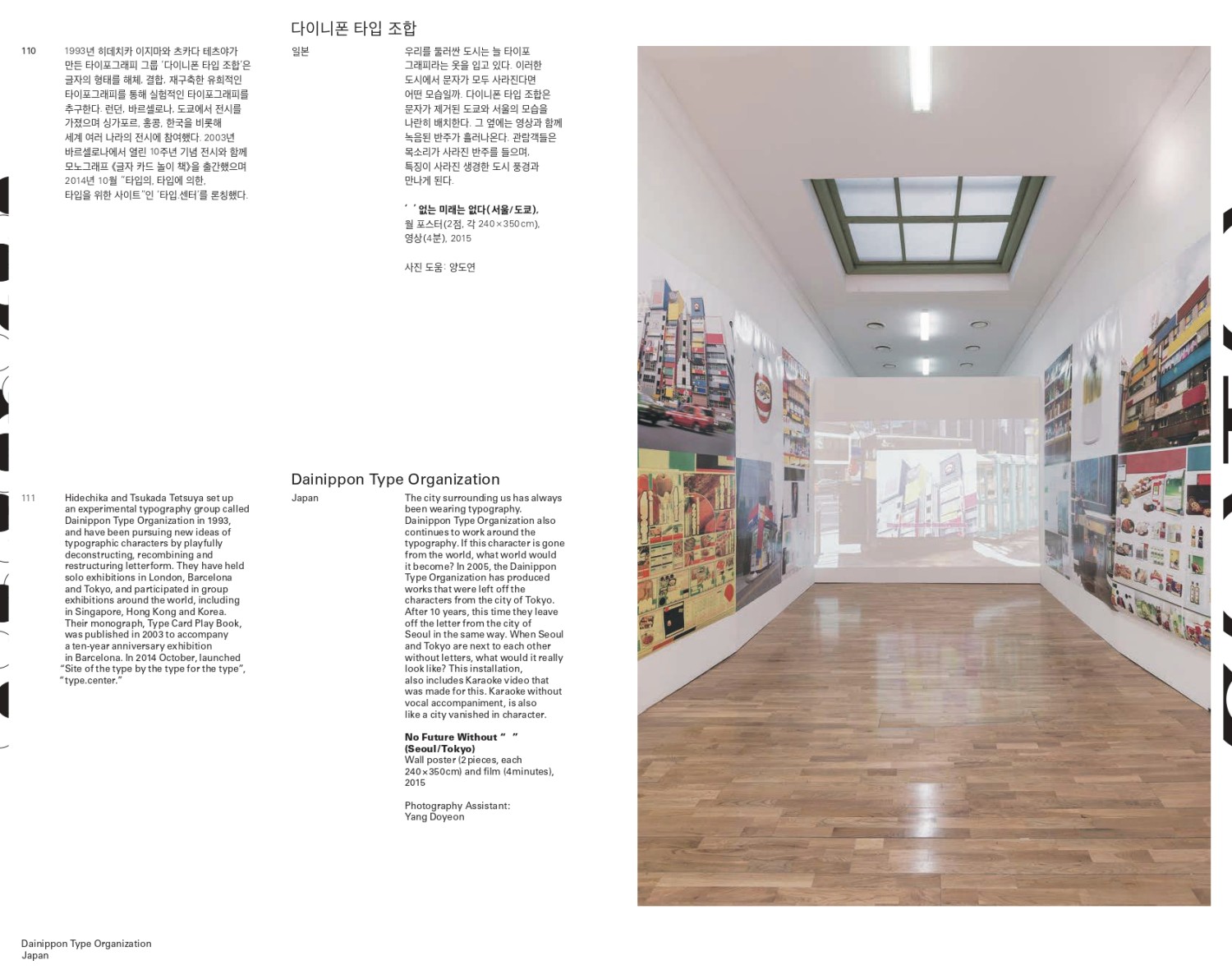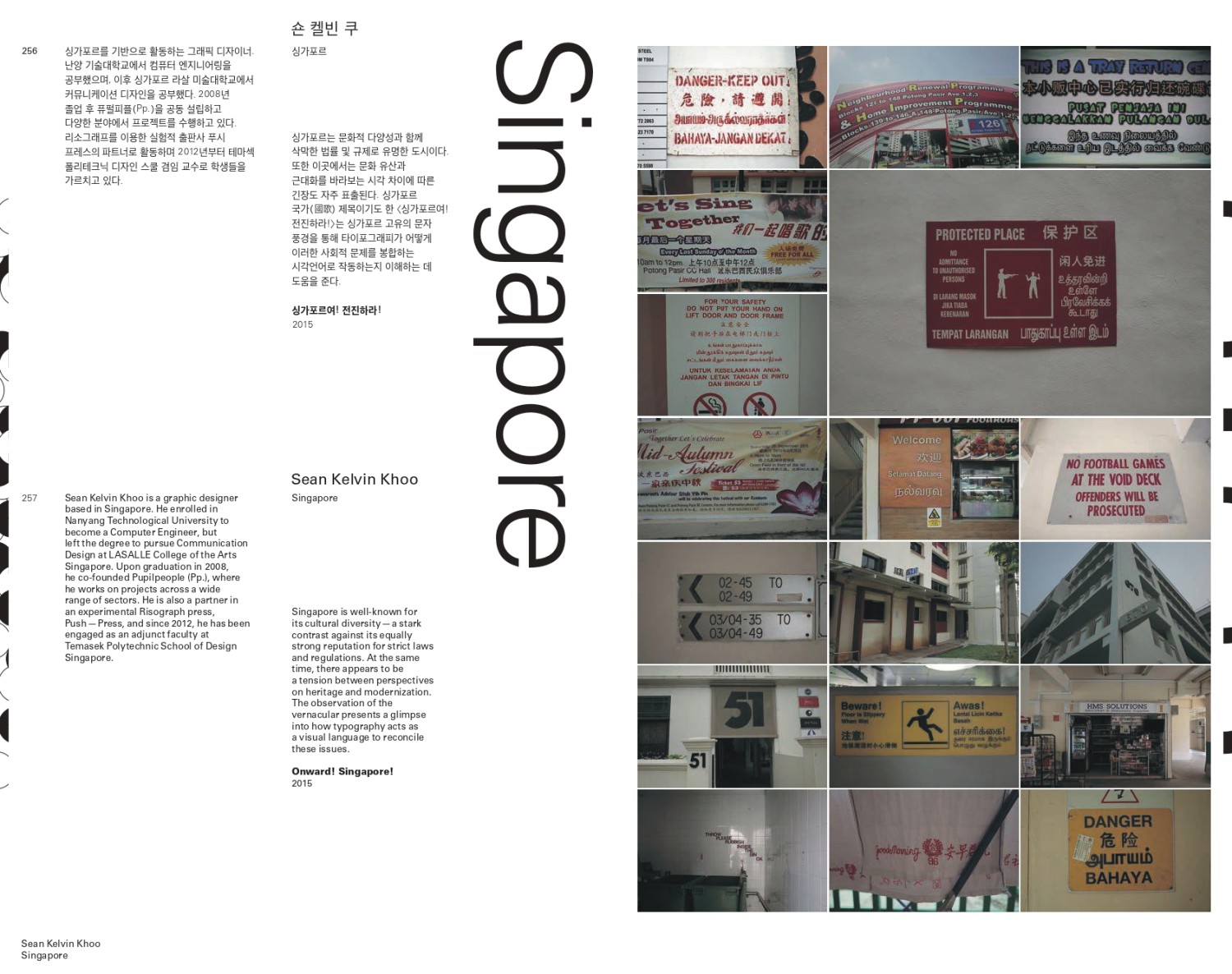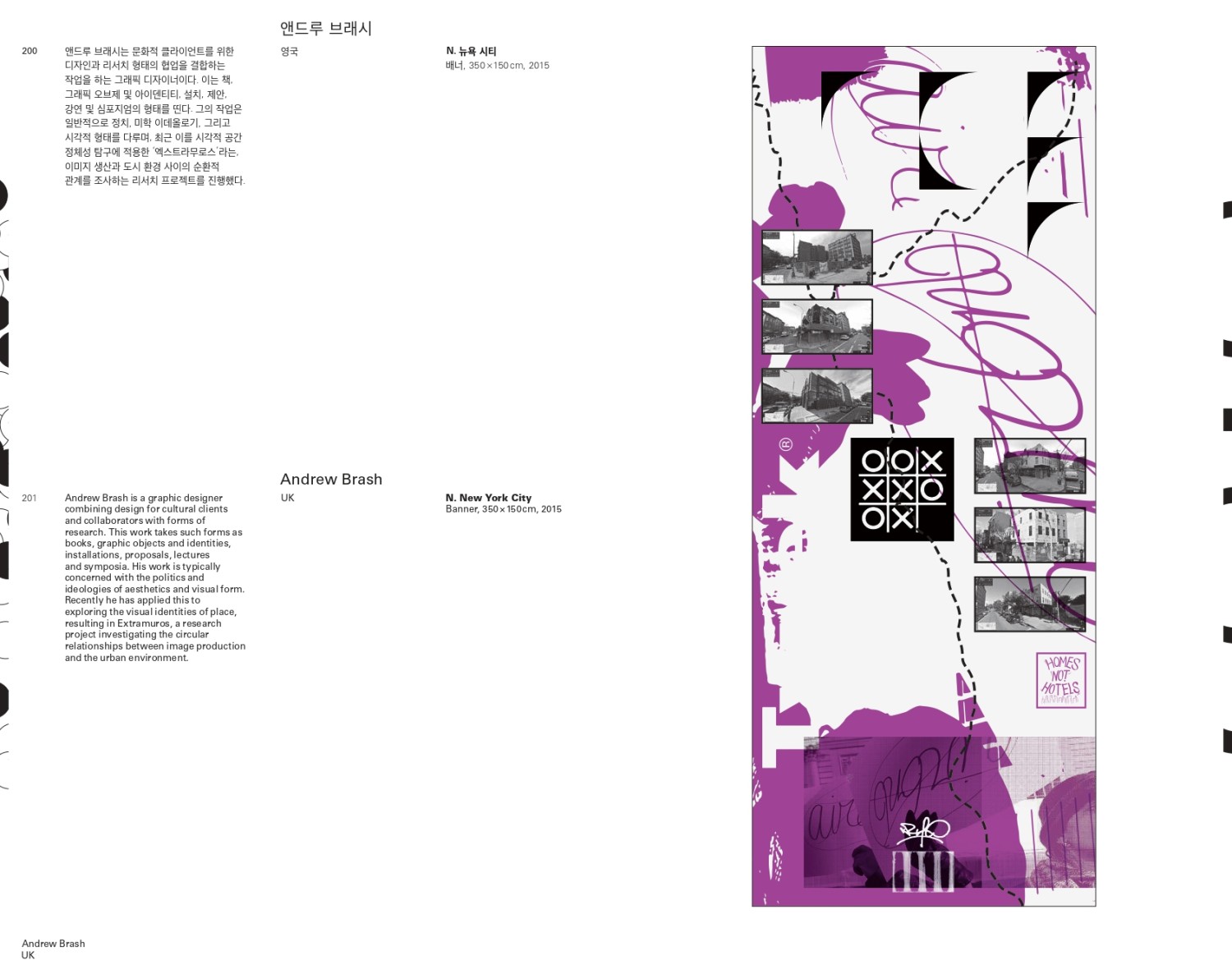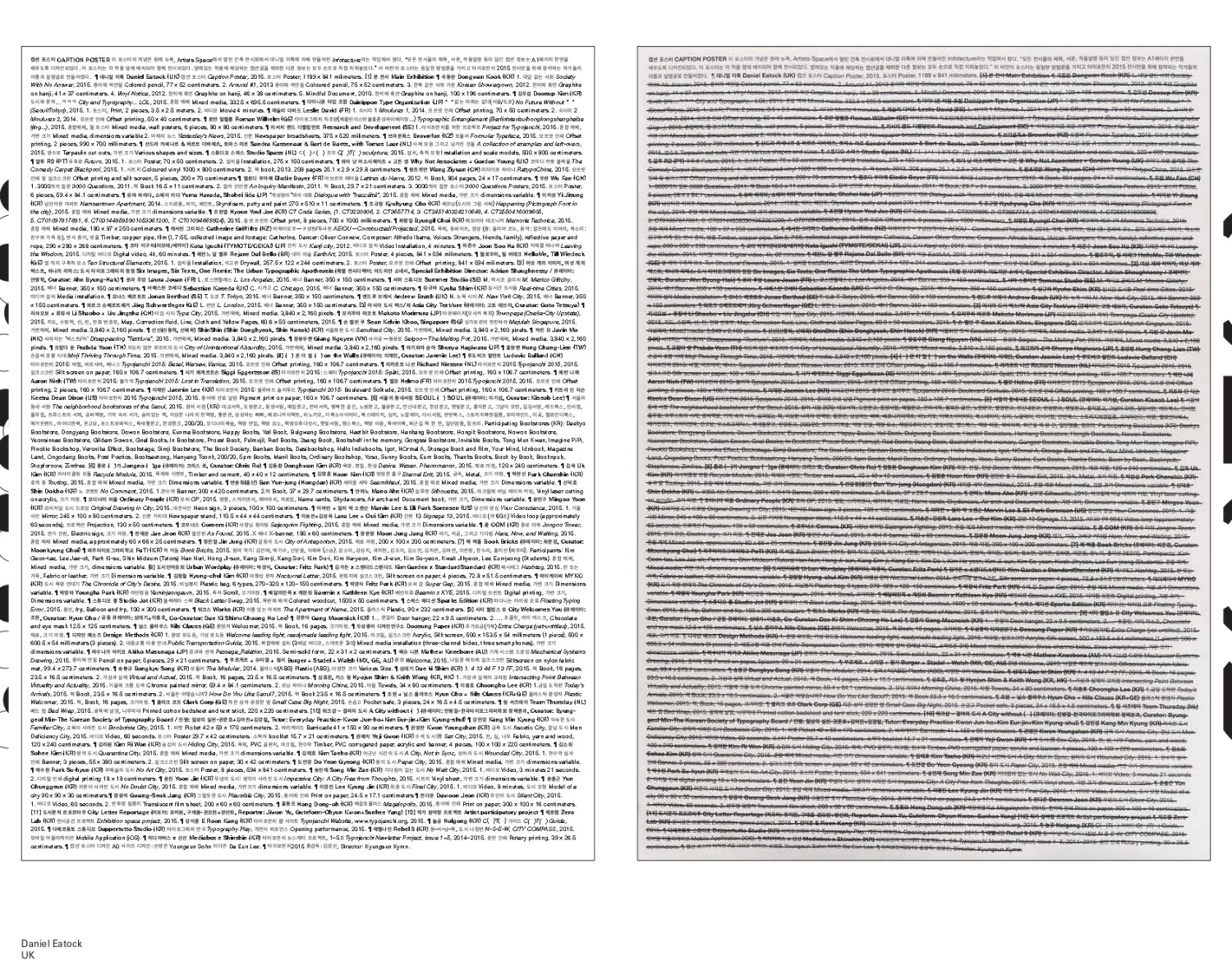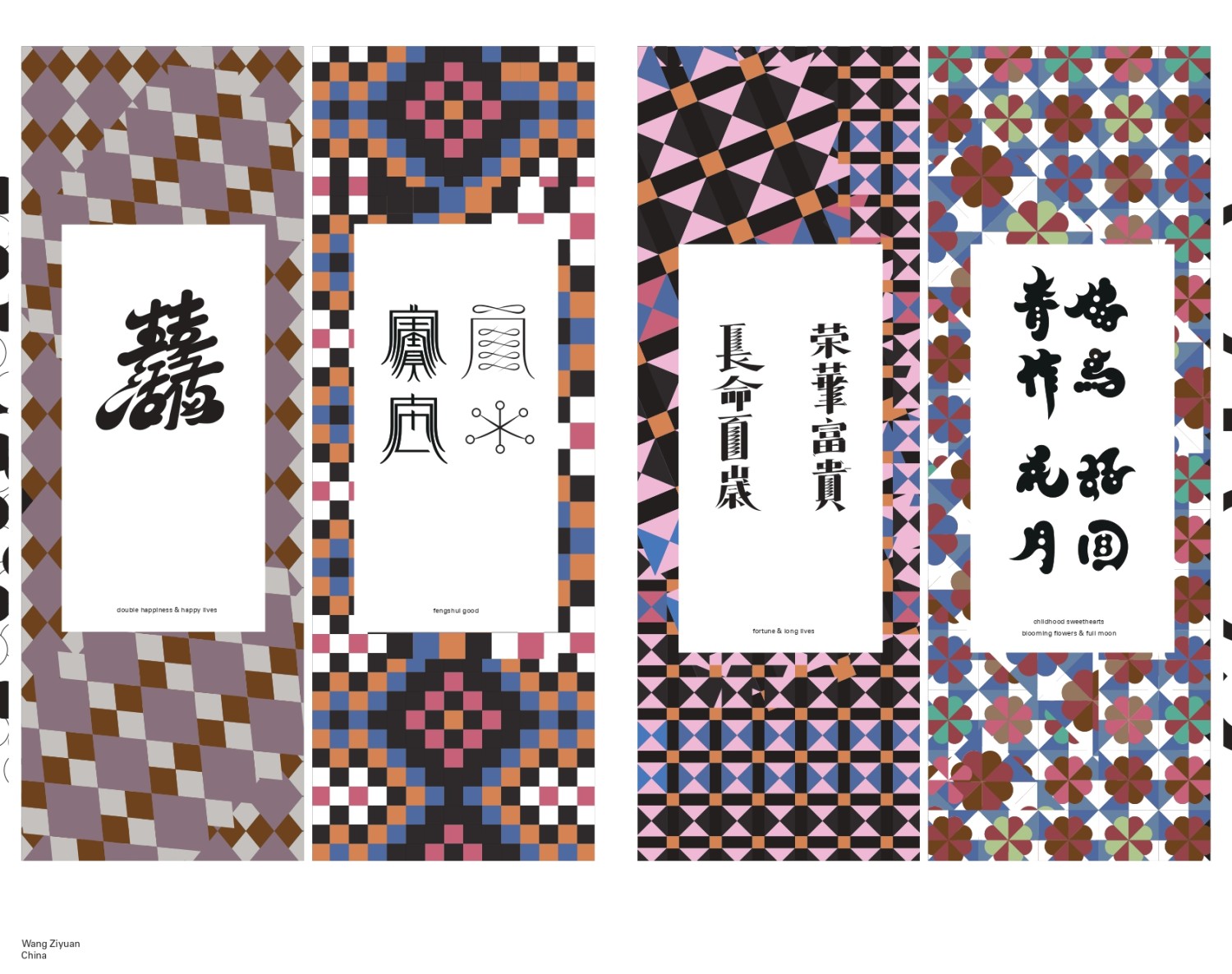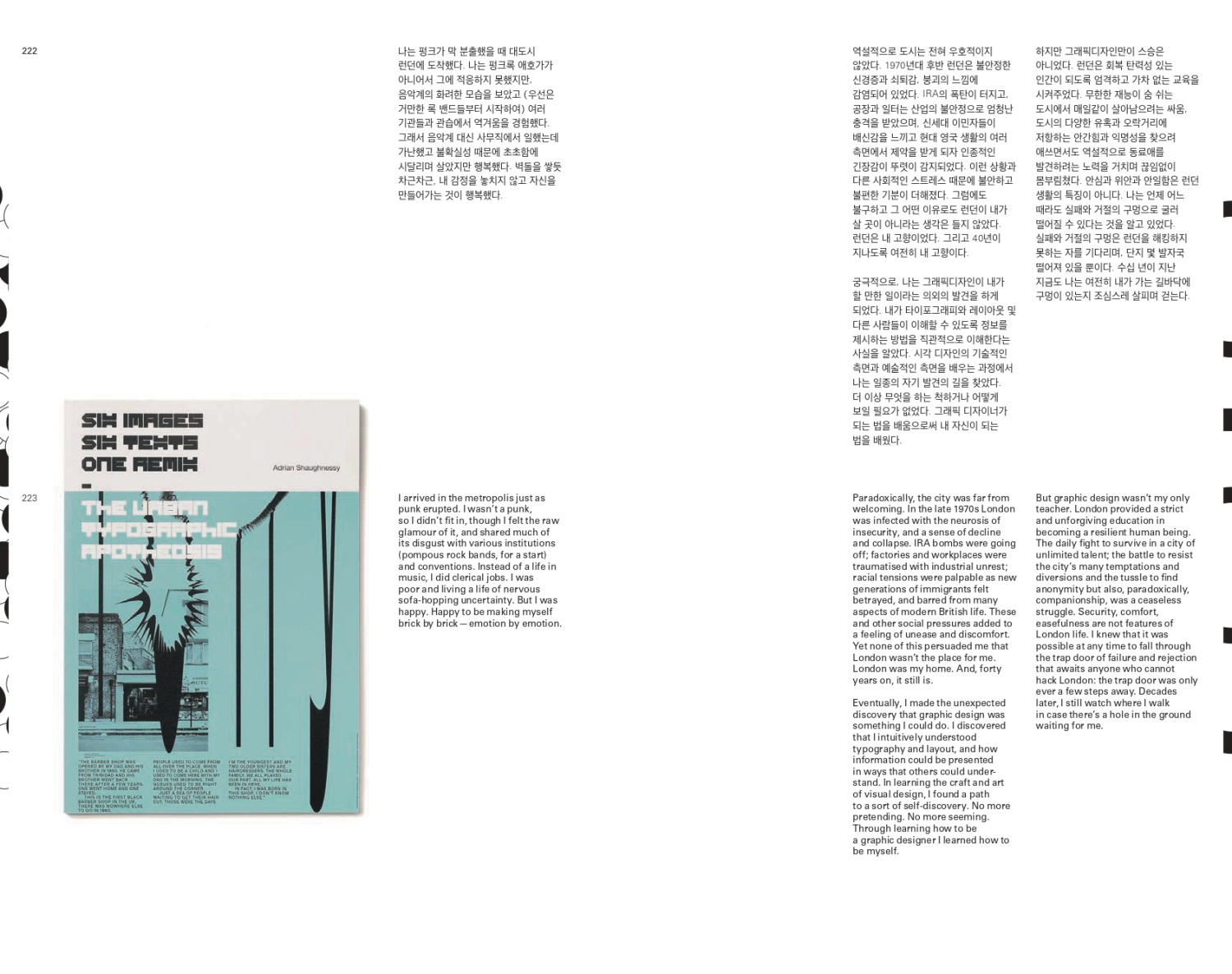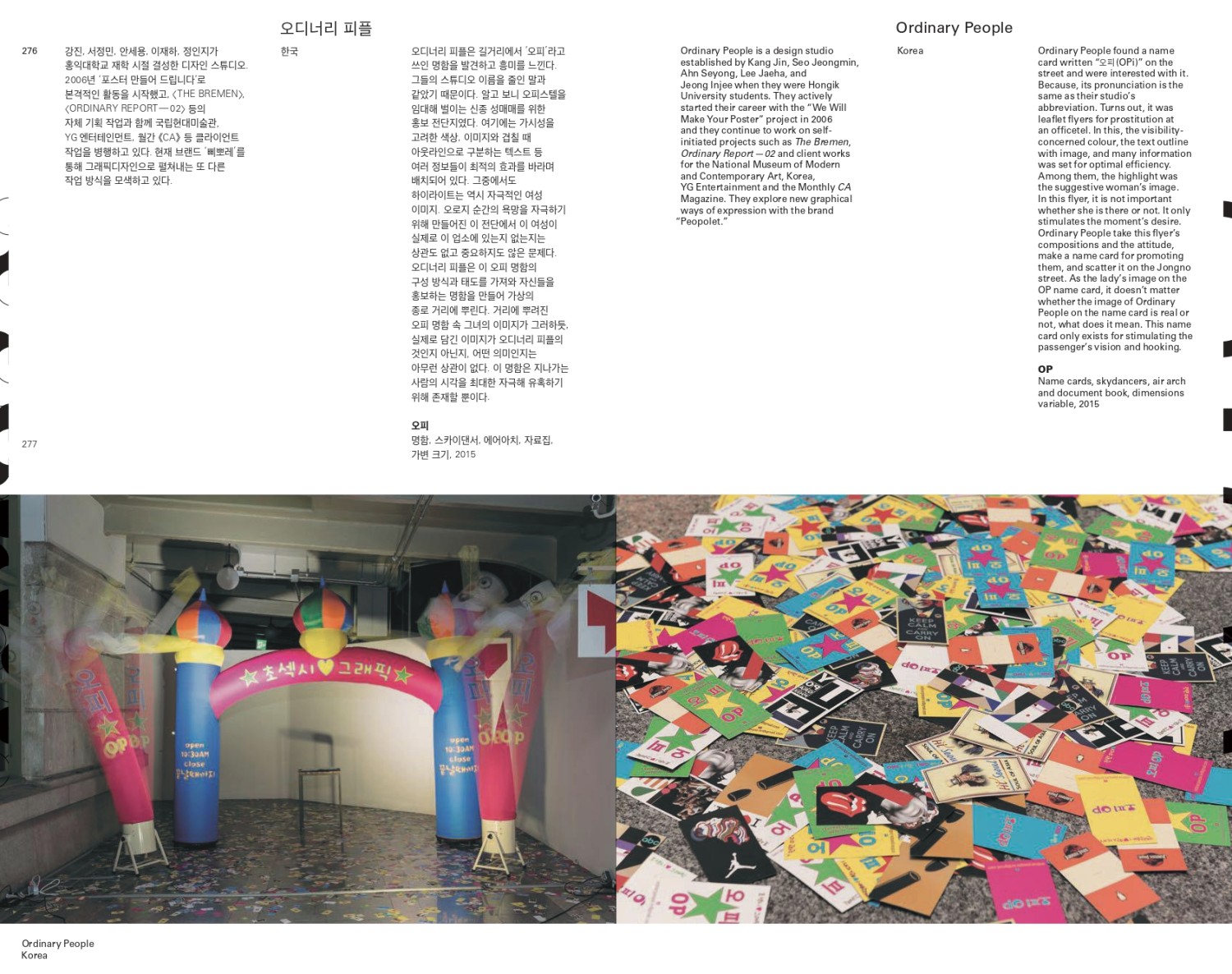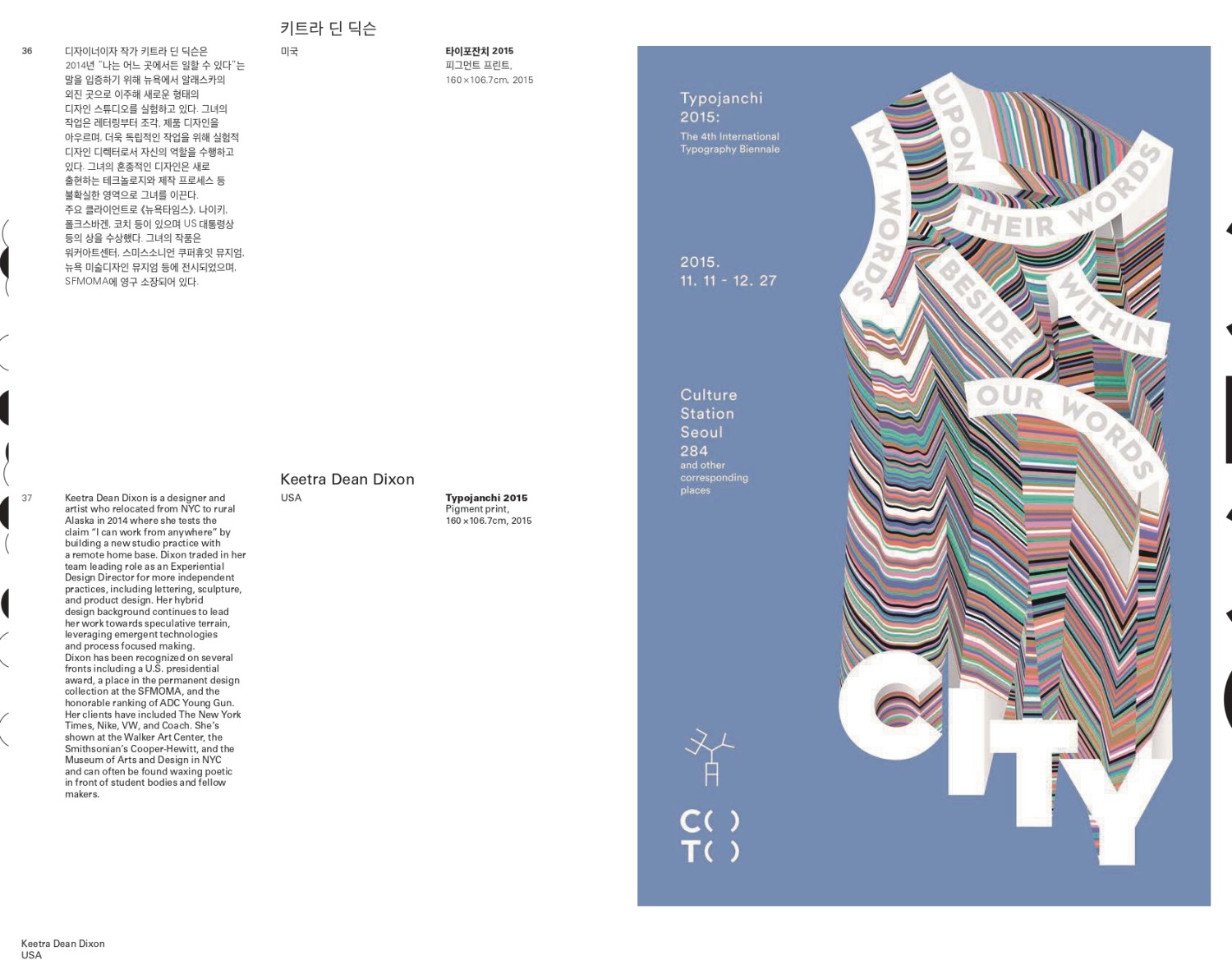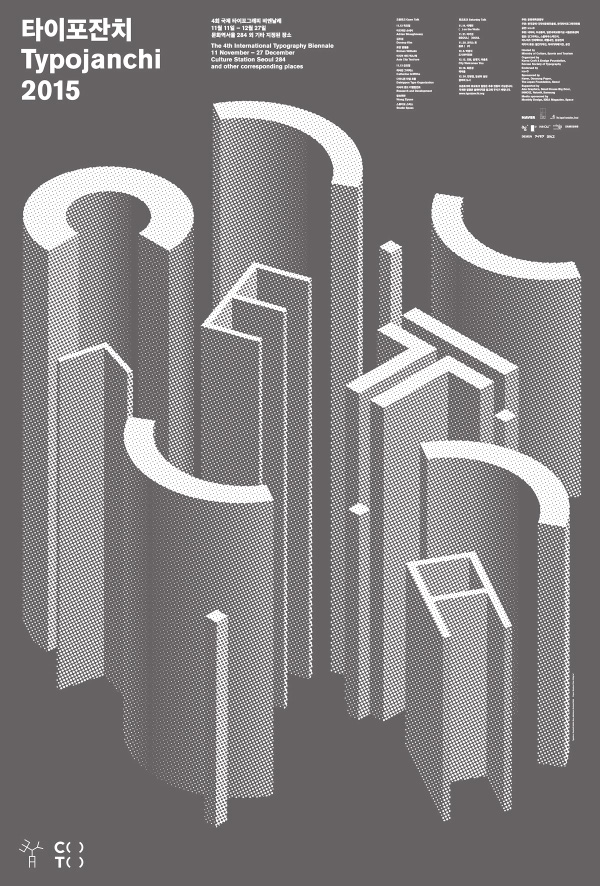
타이포잔치 2015: C( )T( )
- 문자와 도시
- 문화역서울 284 외 국내외 지정 장소
- 2015년 11월 11일 – 2015년 12월 27일
도시를 걷는다는 것은 문자를 읽는 일이다. 4회 타이포잔치는 《C( )T( )》라는 암호 같은 제목 아래, 도시와 문자가 어떻게 서로의 형태가 되는지를 탐색했다. ‘문자와 도시’라는 주제를 통해 활자는 간판과 표지판을 넘어 도시 경험의 감각이자 구조가 되었다. 문화역서울 284를 중심으로 국내외 다양한 장소에서 펼쳐진 전시는, 본전시와 특별 전시, 연계 전시, 워크숍, 강연, 출판 등으로 구성되어 도시 공간 속 타이포그래피의 다층적인 역할을 조망했다. 전 세계 90팀의 디자이너들이 참여하여, 도시라는 무대 위에 문자로 구축된 풍경을 제안했다. 총감독 김경선의 기획 아래, 이번 비엔날레는 작가 수, 작품 영역, 관람객 수, 후원 규모까지 이전보다 한층 확대되며 명실상부 세계 유일의 타이포그래피 비엔날레로 자리매김했다. 관람객 수는 4만 명을 넘어섰고, 전시 아이덴티티는 ‘Core77 Design Awards 2016’을 수상하며 국제 디자인계에서도 주목받았다. 또한 이번 타이포잔치는 국립한글박물관에 아카이빙을 위한 기증이 이루어지며, 타이포그래피 비엔날레의 기록성과 역사적 가치를 새롭게 정립하는 계기가 되었다. 《C( )T( )》는 도시의 틈새에 놓인 문자의 가능성을 불러낸 사건이었다. 그 빈칸은 지금도, 누군가의 시선과 상상으로 채워지고 있다.